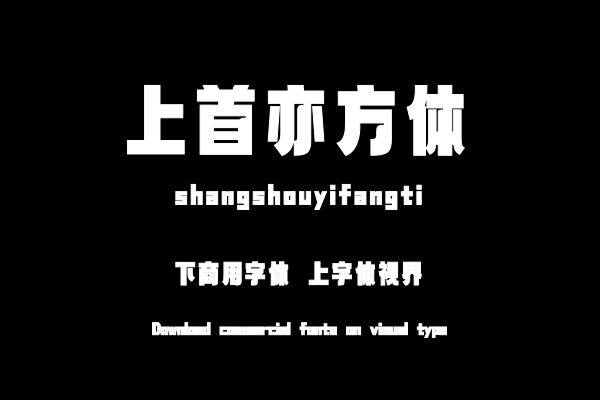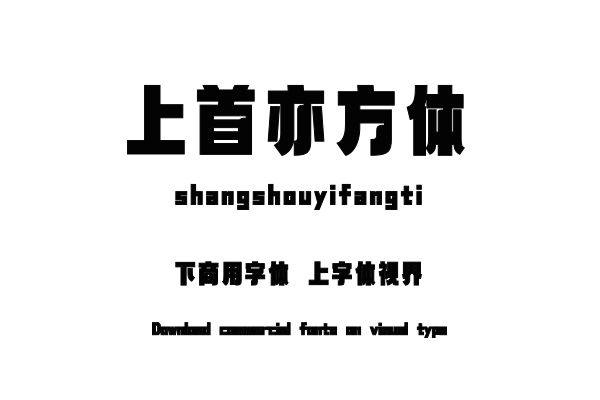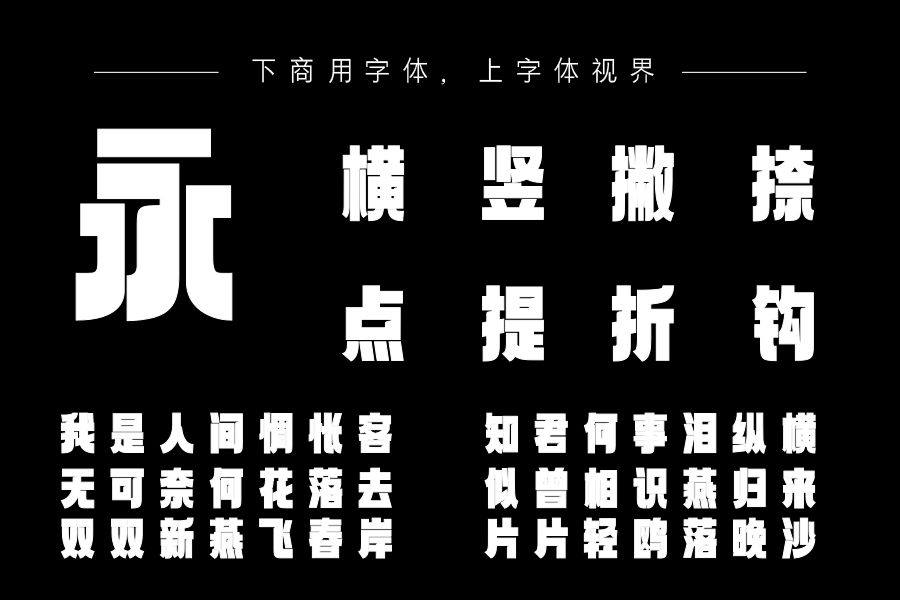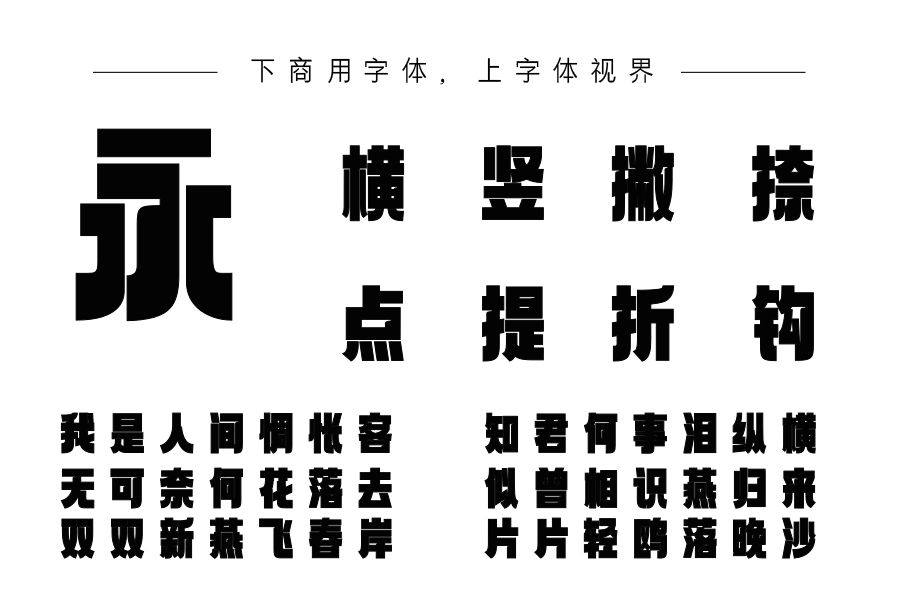
上首亦方体,字体整体方正稳重,字形高挑。高挑的字形以及笔画间的锲口又使得字体增添一分活泼灵动。笔画整体采取简单几何形状组成,粗细上横竖笔均衡且整体偏粗,使得字体......购买须知:“下载服务费”与“字体VIP”所获得字体 仅用于个人非商用, 商用请联系付费授权。本字体为电脑用字,手机没有root权限不支持直接手机换字(手机如何root,请自行百度搜索教程)。购买前请先 了解清楚后再付款 ,字体为虚拟产品无法回收 一旦购买不支持退款。